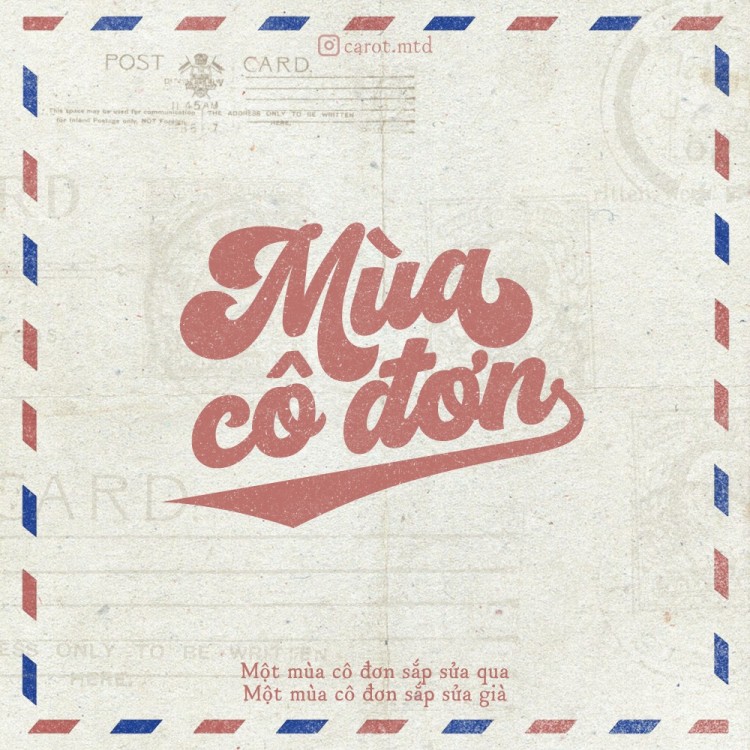
Giới thiệu về Font việt hóa MTD Groovy Script
Trong thế giới thiết kế đồ họa hiện đại, việc tìm kiếm một bộ Font Chữ mang phong cách retro nhưng vẫn đảm bảo tính ứng dụng cao là điều vô cùng quan trọng. Font việt hóa MTD Groovy Script chính là sự lựa chọn hoàn hảo cho những ai yêu thích vẻ đẹp phóng khoáng và đầy cá tính. Đây là một bộ font dạng script với các đường nét uốn lượn mềm mại, mang đậm hơi thở của thập niên 70. Nhờ quá trình việt hóa chỉn chu từ đội ngũ MTD, người dùng tại Việt Nam có thể dễ dàng sử dụng bộ font này để gõ tiếng Việt có dấu mà không lo lỗi hiển thị hay mất nét.
Đặc điểm nổi bật của MTD Groovy Script
Font việt hóa MTD Groovy Script sở hữu cấu trúc dày dặn, giúp các thiết kế trở nên nổi bật và thu hút thị giác ngay lập tức. Các ký tự được thiết kế với độ tương phản cao, tạo cảm giác chuyển động mượt mà như những nét vẽ thủ công bằng cọ. Đặc biệt, bộ font này cung cấp nhiều ký tự thay thế (alternates) và các đường nét nối chữ tinh tế, giúp các nhà thiết kế tự do sáng tạo trong việc tạo hình typo hay thiết kế bìa sách, áo thun và logo. Sự kết hợp giữa phong cách cổ điển và tính năng kỹ thuật hiện đại giúp font này luôn giữ được sức hút riêng biệt.
Ứng dụng Font việt hóa MTD Groovy Script trong thiết kế
Với vẻ ngoài rực rỡ và tràn đầy năng lượng, font chữ này thường được ứng dụng rộng rãi trong các dự án sáng tạo đòi hỏi sự độc đáo. Bạn có thể sử dụng nó để trang trí thiệp mời, làm banner quảng cáo cho các sự kiện âm nhạc hoặc tạo tiêu đề cho các video blog cá nhân. Đối với các bạn học sinh và sinh viên, đây cũng là công cụ tuyệt vời để làm bài thuyết trình hoặc thiết kế báo tường sinh động hơn. Sự linh hoạt của font giúp nó dễ dàng tương thích với nhiều phần mềm đồ họa phổ biến hiện nay.
Kết luận về bộ font độc đáo này